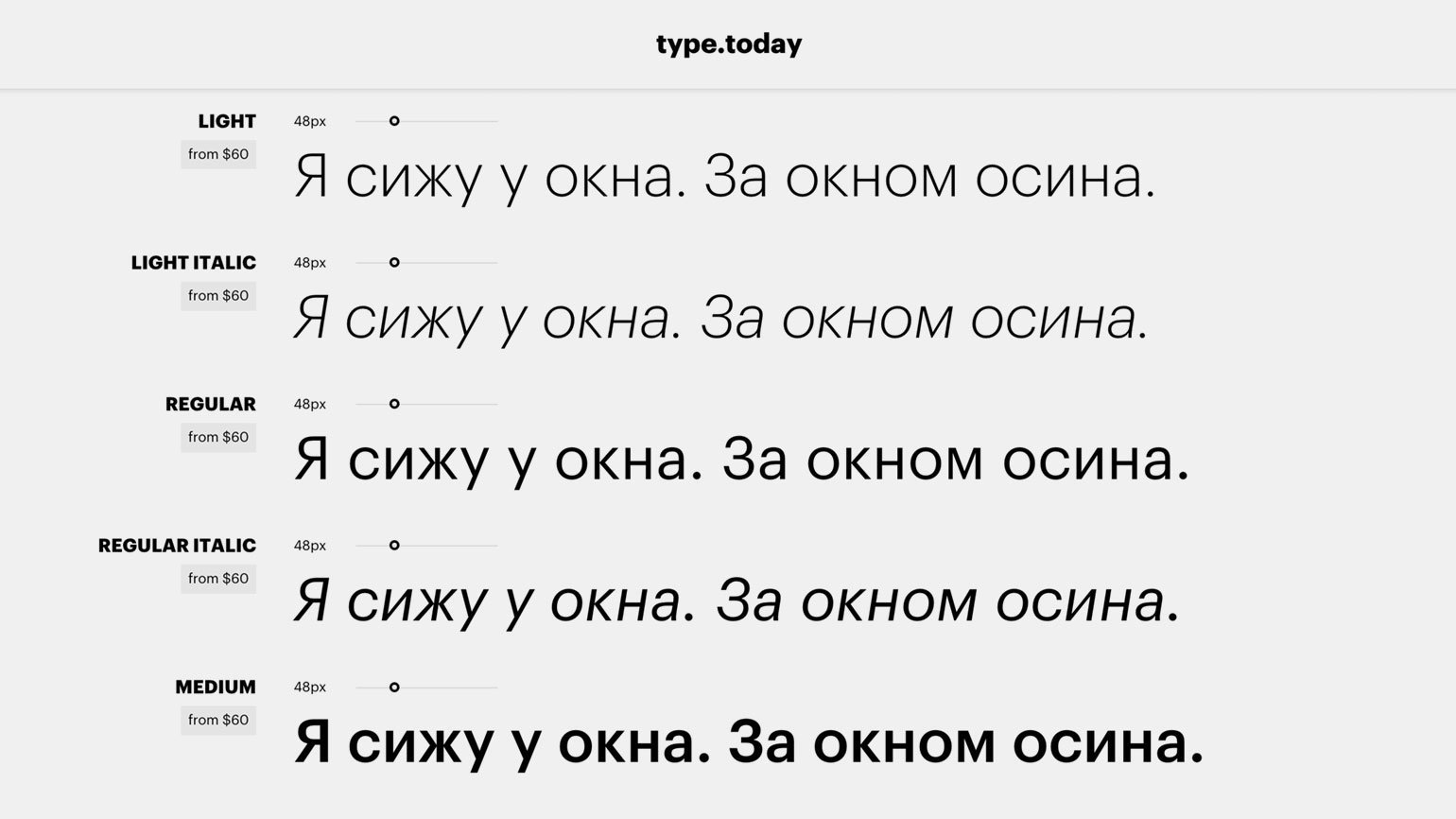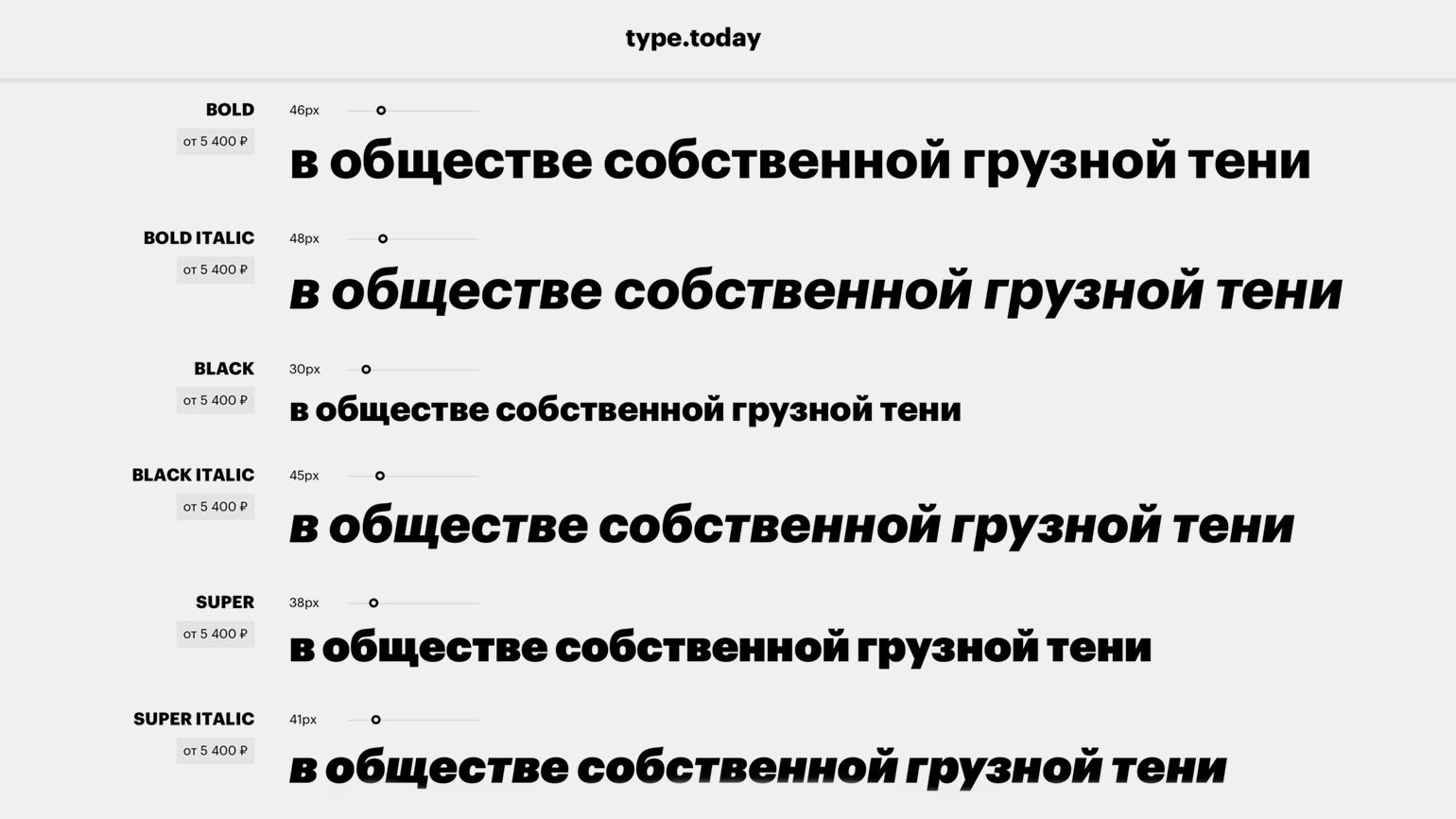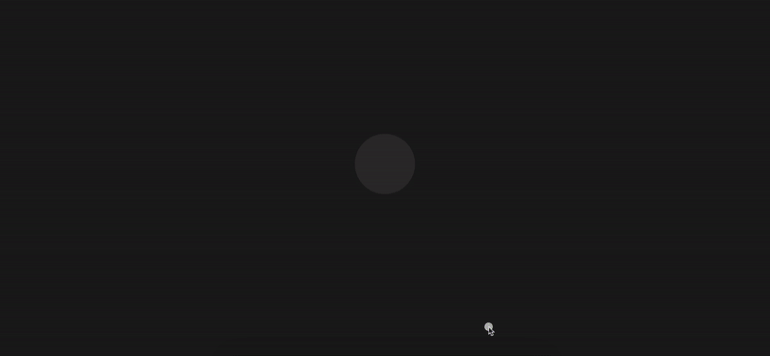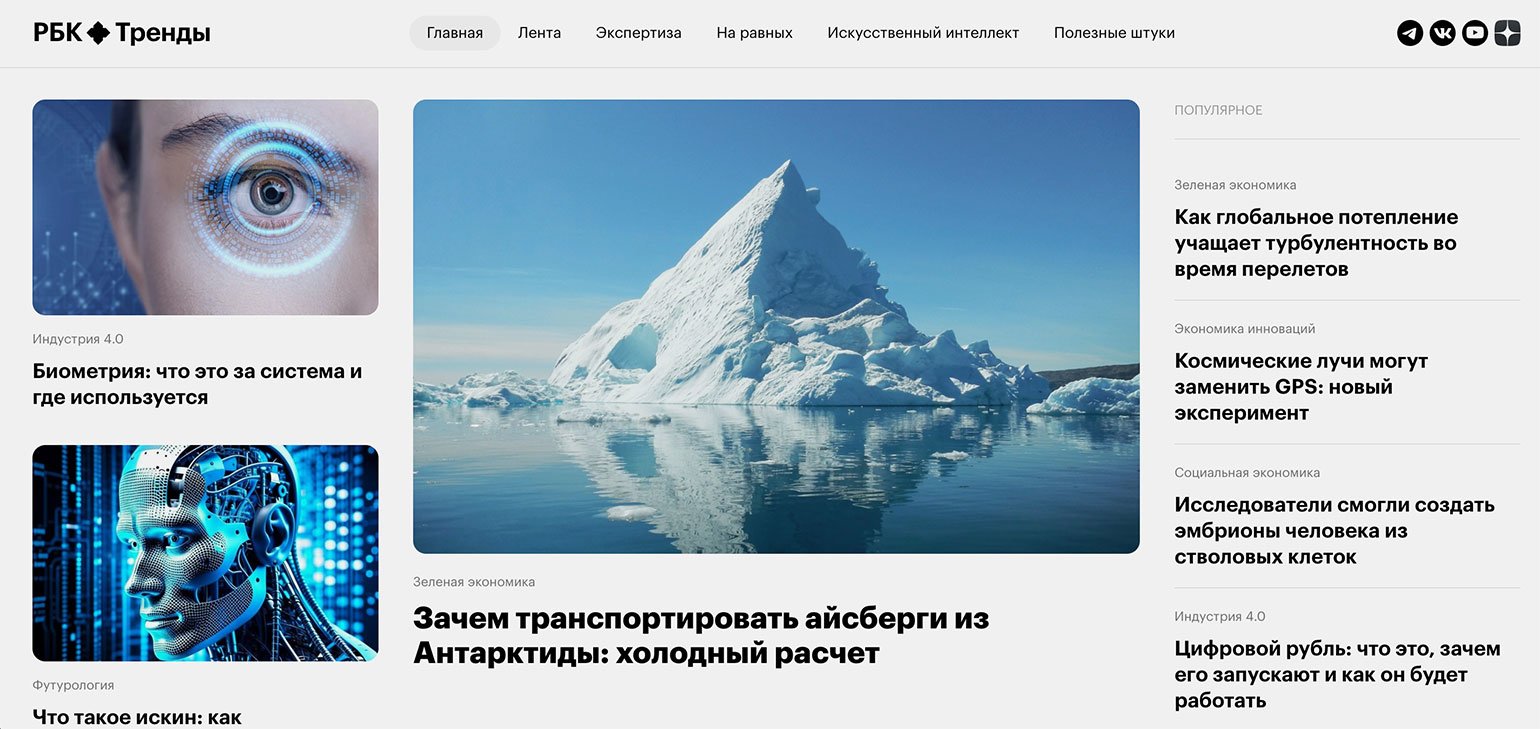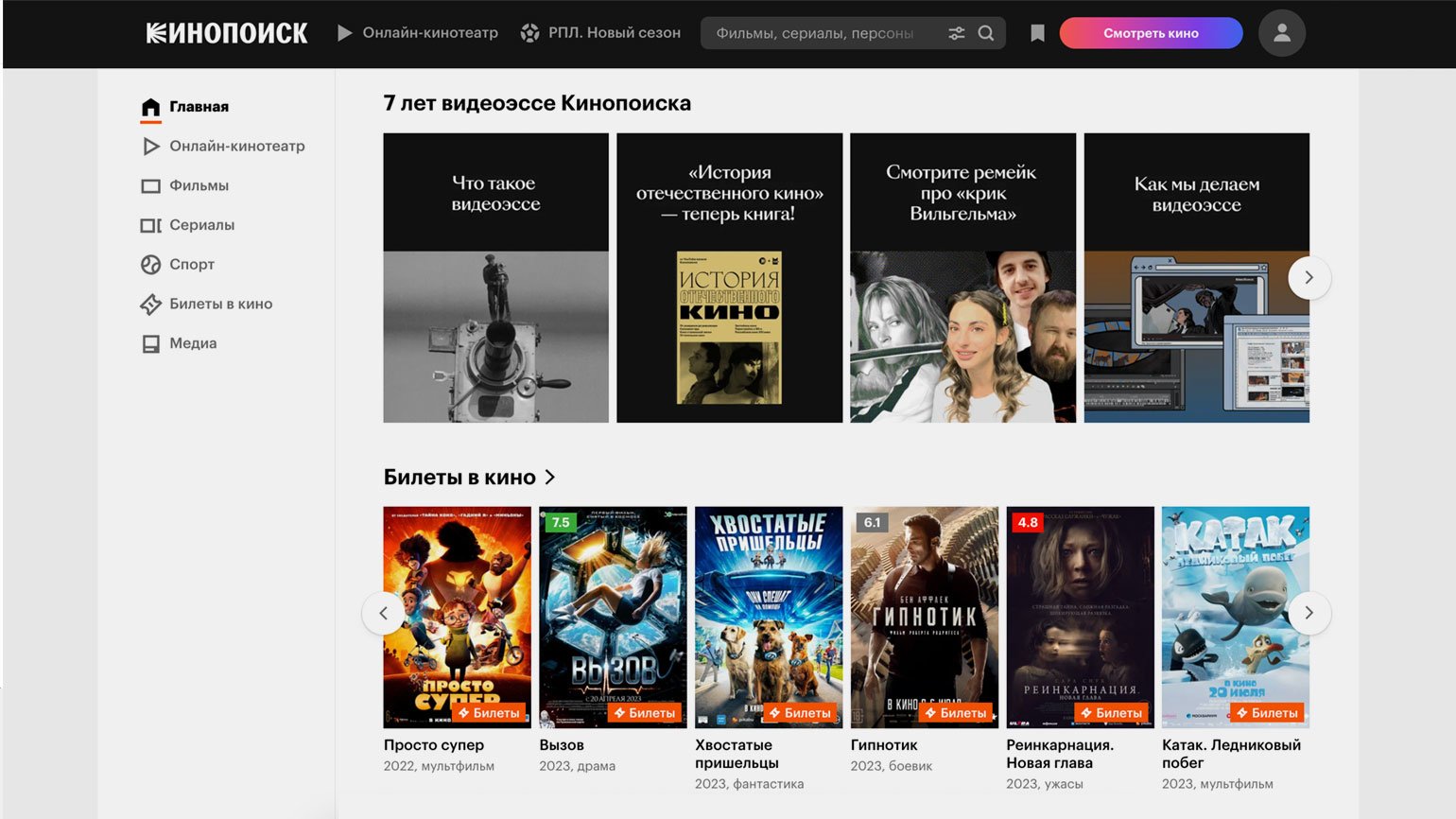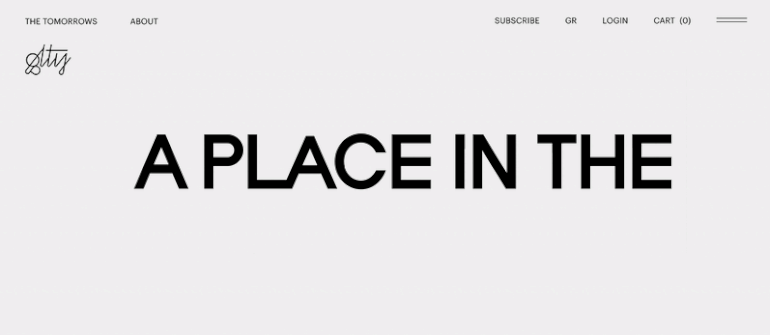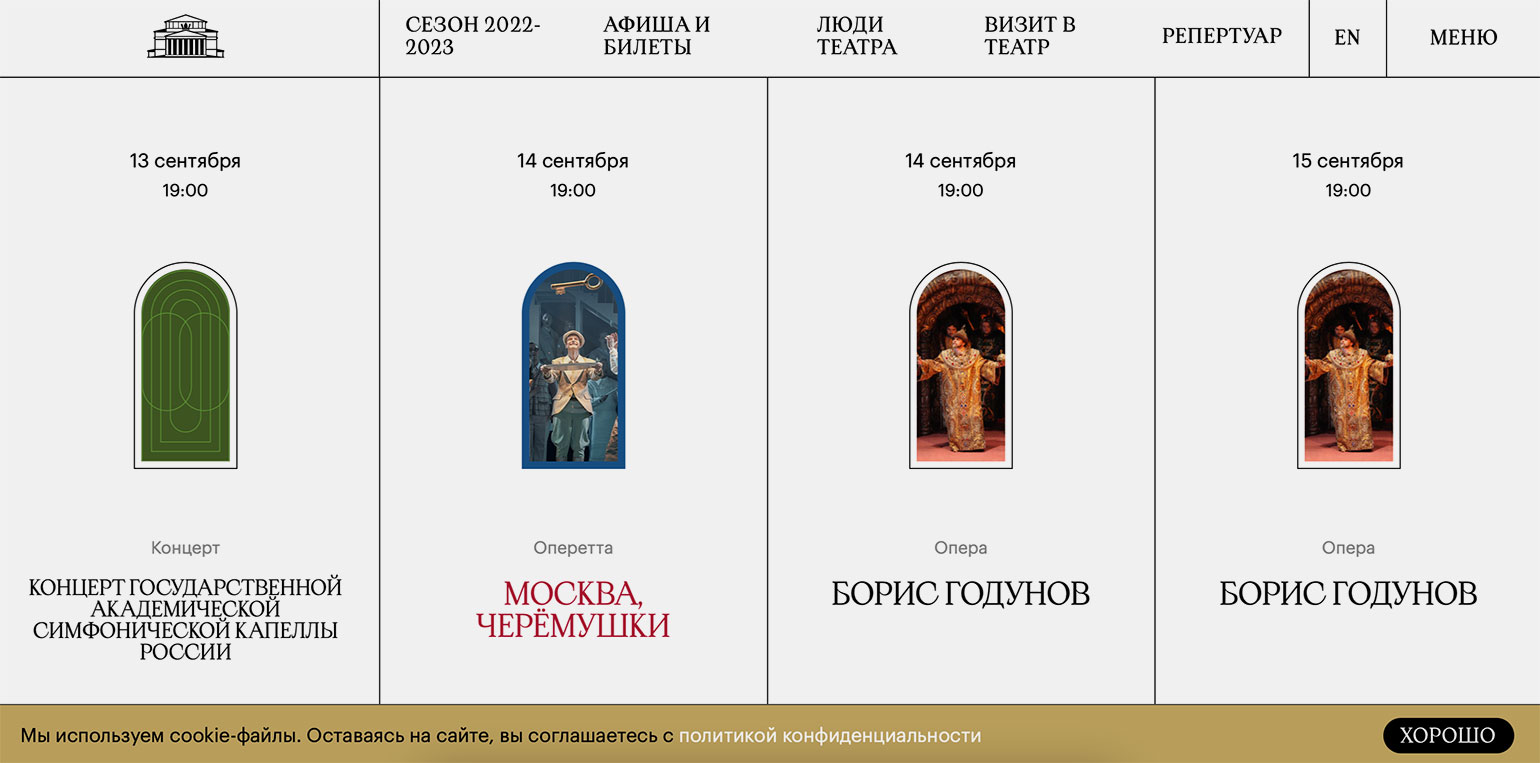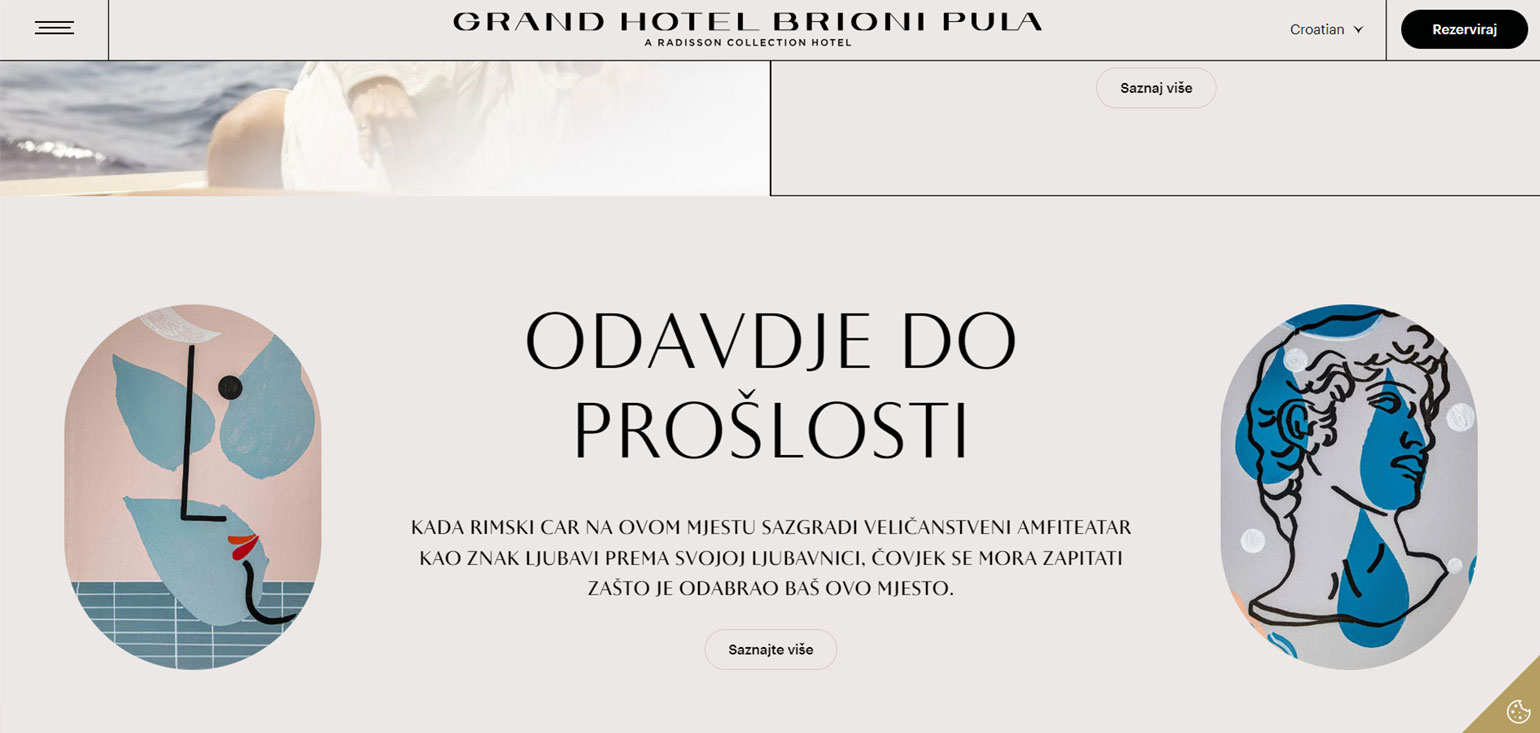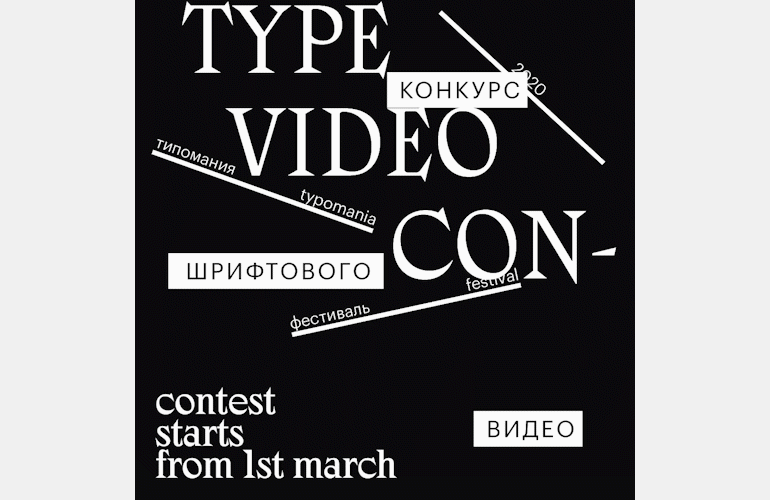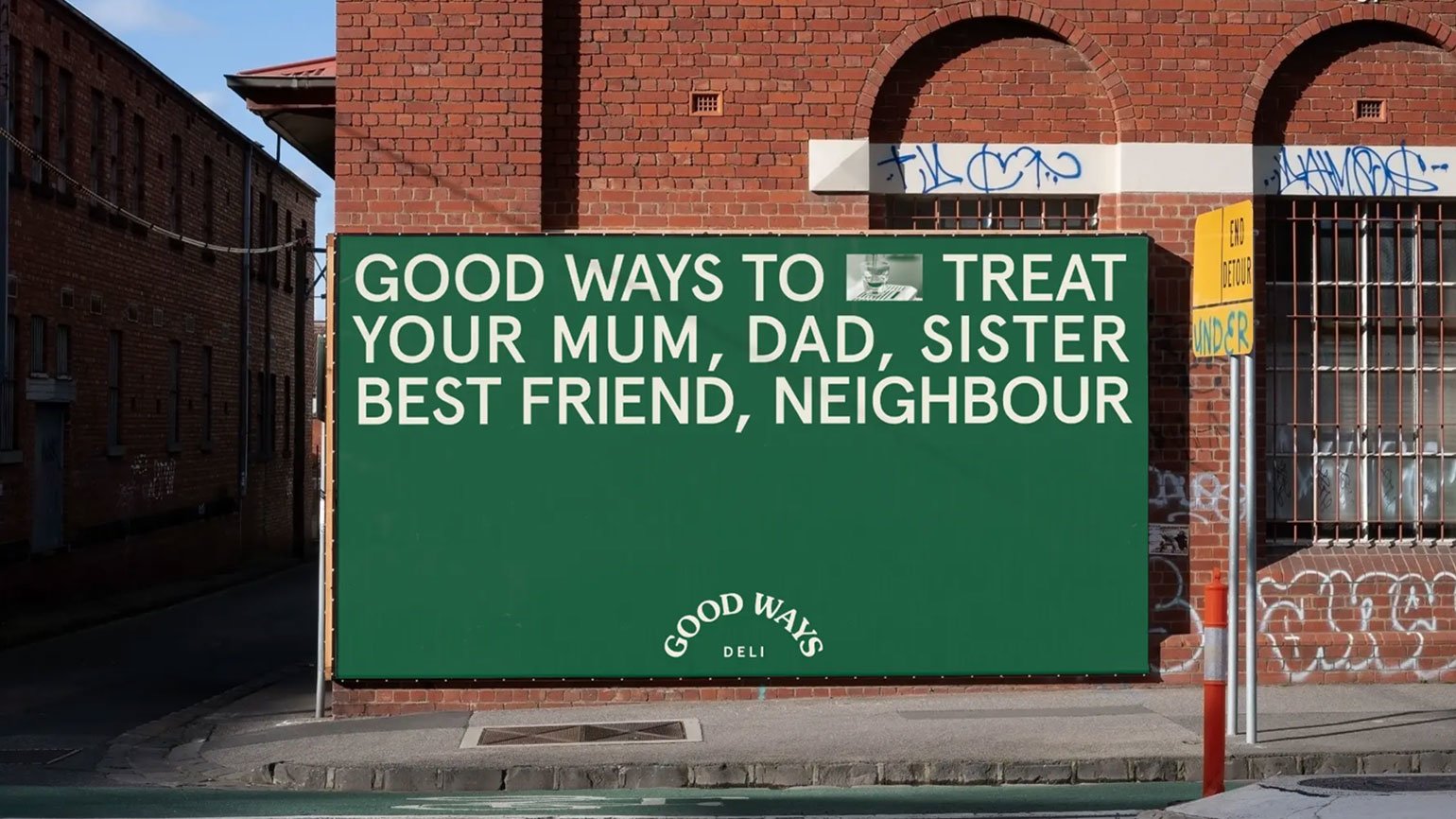
Шрифт Graphik: где используют и с чем сочетают
Рассказываем, для каких проектов подходит Graphik, и показываем примеры удачных шрифтовых пар с ним.
Создать эффектную типографику для сайта, документа, постера или рекламы непросто. Правильное решение очень важно: шрифты влияют на восприятие текста и изображений, они способны и привлекать, и отталкивать. К тому же их много, и даже если для проекта уже выбран основной шрифт, к нему наверняка понадобятся дополнительные.
Разберём модную современную гарнитуру Graphik и расскажем, с чем её сочетать.
Graphik — что это за шрифт
Graphik — это семейство гротесков из девяти начертаний (от сверхтонкого Thin до сверхжирного Super) и девяти соответствующих им курсивов.
Graphik вышел в 2009 году. Его автор — нью-йоркский дизайнер Кристиан Шварц — разрабатывал эти шрифты для собственной айдентики. Он хотел создать очень гладкий, но достаточно тёплый гротеск:
Важно было создать шрифт, который легко адаптируется к любому контексту и у которого нет явной привязки к какому-либо конкретному периоду в истории графического дизайна. В итоге я черпал вдохновение во всех периодах XX века.
Идея создать ещё один универсальный и «никакой» гротеск пришлась ко времени. В результате Кристиан дорабатывал этот проект по заказу дизайнеров Роберта Приста и Грейс Ли для Condé Nast Portfolio и делал дополнительные начертания для ребрендинга журнала Wallpaper*. После этого весь объём Graphik стал широко распространяться.
На рисунок знаков Graphik во многом повлияла типографика швейцарских постеров середины XX века и шрифты из «списка Б»:
Меня больше вдохновляли не особенно популярные гротески, кои во множестве выпускали европейские словолитни в качестве конкурентов могущественным Futura, Helvetica и Univers — например, Neuzeit Grotesk, Folio, Recta и Maxima. Ни один из них не был прорывным, но у многих из них была своеобразная прелесть.
В 2015 году Илья Рудерман выпустил кириллическую версию Graphik.
К 2018 году Graphik стал членом суперсемейства: вышли ещё шесть версий с зауженной графикой от Compact до XXXX Condensed, версия Wide, а также гарнитура для арабского письма.
Благодаря «чистому» характеру Graphik стал популярным инструментом в digital-дизайне. В его рисунке нет отсылок к этническим или культурным элементам, поэтому он способен стать решением почти любой задачи и основой почти любой типографики — и выразительной, и технически-заурядной.
Graphik незаметно определил эстетику многих современных медиа: он и достаточно элегантный, и несложный, и конвенциональный, и без флёра официальности. К тому же он легко читается в любом размере. Например, эти шрифты — основа айдентики и фирменной типографики медиахолдинга РБК.
С Graphik несложно составлять эффектные шрифтовые пары. Например, можно брать шрифты разной насыщенности этой гарнитуры: из-за того, что графика тонких и нормальных начертаний Graphik ближе к Neuzeit Grotesk, а жирных — к Plak, они визуально отличаются и при этом выглядят родственными.
Кроме того, неизысканная эстетика этого гротеска не подавляет декоративные каллиграфические и акцидентные шрифты и позволяет ярче сиять даже привычным антиквам.
Посмотрим, как шрифты Graphik выглядят в разных проектах.
Graphik в интерфейсах
GLTY — проект Димитриса Гкациса. Он работает в Афинах, создаёт лимитированные объекты с продуманным оптимистичным дизайном и использует только экологичные материалы. И ещё — ориентируется на тех, кто больше ценит интересные истории, чем владение материальными вещами.
Тексты в интерфейсе оформлены только шрифтами Graphik, и минималистичность типографики подчёркивает и расцвечивает подвижный леттеринг.
Изображение: сайт glty / Skillbox Media
Сайт Большого театра полностью обновили в 2021 году. За редизайн отвечала команда Sulliwan Studio.
В основе digital-типографики — шрифтовая пара Apoc и Graphik. Современной антиквой с асимметрией и острыми засечками оформлены заголовки первого и второго уровня, а простым гротеском, который легко читать, — интерфейсные элементы с более «техническими» текстами: пояснениями, подписями, датами.
Скриншот: сайт «Большой театр» / Skillbox Media
В шрифтах Graphik есть намёк на элегантность, поэтому они отлично подходят для интерфейсов премиальных сервисов.
Например, как на этом сайте для бронирования номеров в отеле на побережье Адриатического моря: заголовки и рекламные призывы оформлены гротеском в романском стиле Astoria Classic Sans, а тексты на кнопках и в футере — Graphik.
Graphik в визуальных коммуникациях
- Neue Haas Grotesk Display. Этот гротеск — возрождённая оригинальная «Гельветика».
- Helvetica Now. Как Helvetica, только лучше — современная, цифровая и чистая.
- Cera Pro. Это тоже гротеск с некоторой теплотой, но с большей геометричностью.
- Founders Grotesk. Эти шрифты — ещё один сплав разных гротесков XX века.